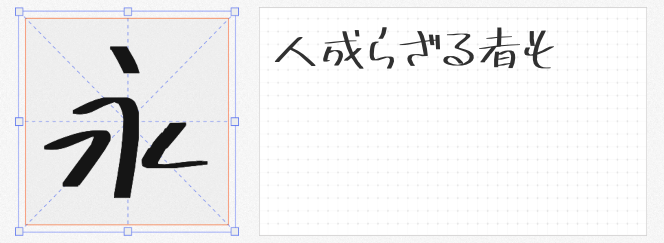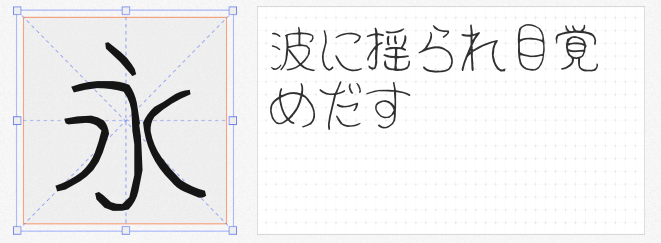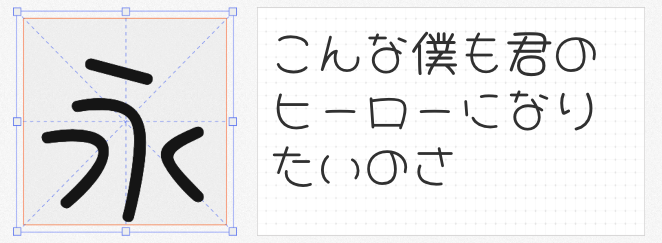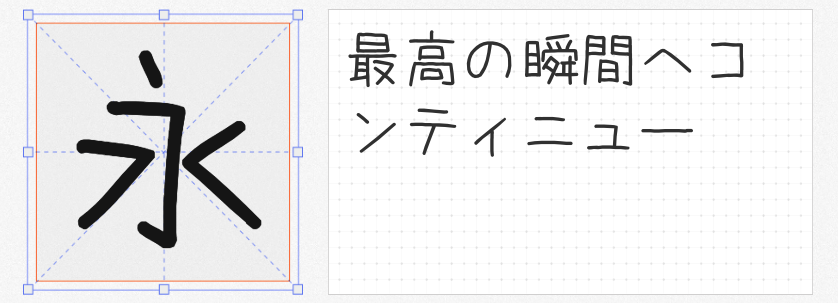
在日系风格设计中,手写字体的温度感与独特性是机械字体难以替代的。本文精选四款免费商用日文字体,涵盖复古、随性、可爱等多元风格,助力设计师在商业项目中实现创意自由。
以1980年代日本流行的“圆形文字”为灵感,八丸POP体将昭和时代的可爱文化与现代设计语言融合。其笔画以圆弧为主导,字母“o”“a”等圆形结构饱满如气球,搭配略微倾斜的轴线,营造出动态的俏皮感。尽管可读性稍弱,但作为标题或装饰性文字时,其复古氛围能瞬间唤醒怀旧情绪。该字体支持JIS一级、二级汉字及IBM扩展字符,覆盖6700余个汉字,兼容中日韩排版需求,适用于包装设计、手账素材及复古主题海报。
红月字体以“不严肃也不可爱”的独特定位脱颖而出。其笔画粗细自然波动,起笔收尾保留毛笔书写的飞白痕迹,仿佛未经修饰的日记手稿。尽管字形纤细,但通过横竖笔画的微妙对比,在保持轻盈感的同时避免了单薄。设计师推荐开启抗锯齿以优化显示效果,适合用于文艺杂志标题、独立品牌包装或需要传递“真实感”的短视频字幕。
由日本设计师軽缶直接描摹手写原稿而成,Maru berry字体保留了书写时的自然抖动与笔画交叉处的墨渍渗透效果。其字形扁宽,重心偏低,字母“n”“m”等闭合结构呈现圆润的椭圆形,搭配略微向右上方倾斜的轴线,传递出慵懒的手作感。该字体支持繁体汉字,适用于咖啡馆菜单、手工艺品标签或需要“去工业化”风格的品牌视觉系统。
由设计师8:51:22 pm创作的851麻花POP体,以“横画加粗、竖画纤细”的对比结构打破传统字体的平衡感。其字形极度扁宽,字母高度被压缩至正常字体的60%,搭配圆润的转角处理,宛如被压扁的棉花糖。尽管官方标注为“随性”,但通过统一的笔画粗细与间距控制,实际使用中仍能保持整齐的视觉节奏。该字体适用于儿童绘本、宠物品牌LOGO或需要强化“萌属性”的社交媒体配图。
设计师可根据项目需求自由组合。这些字体不仅是工具,更是传递日系美学态度的媒介。